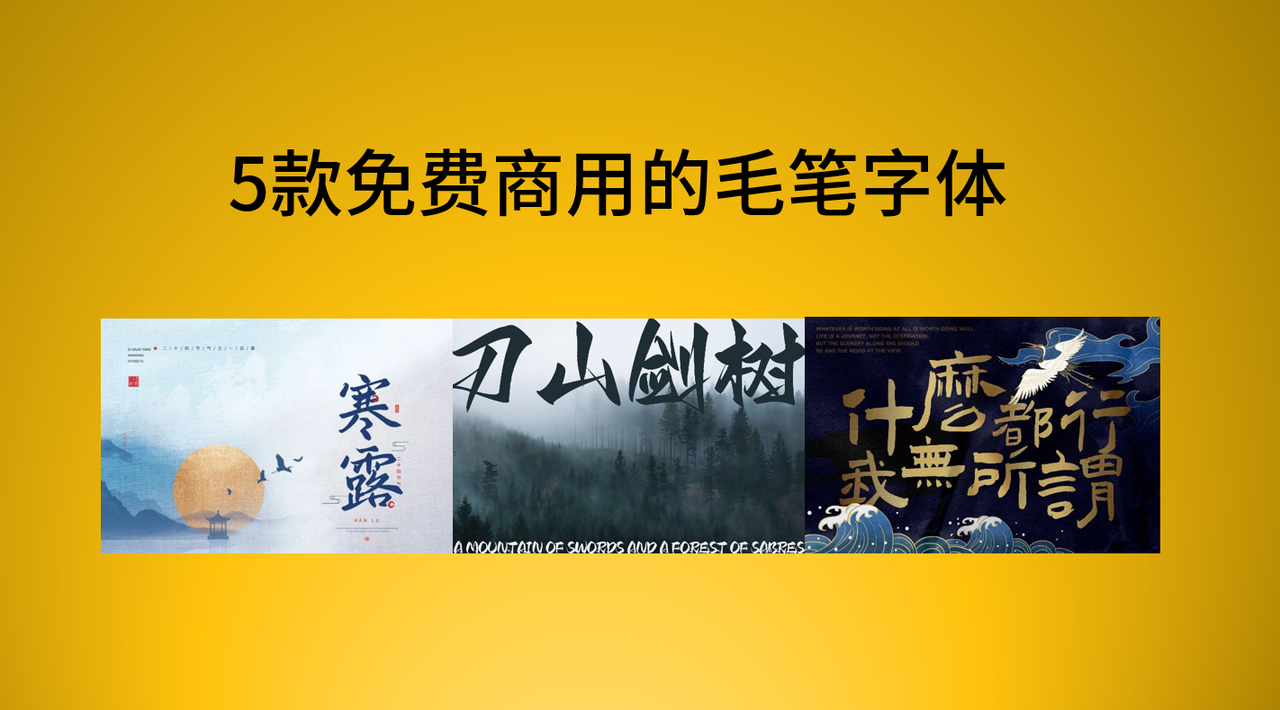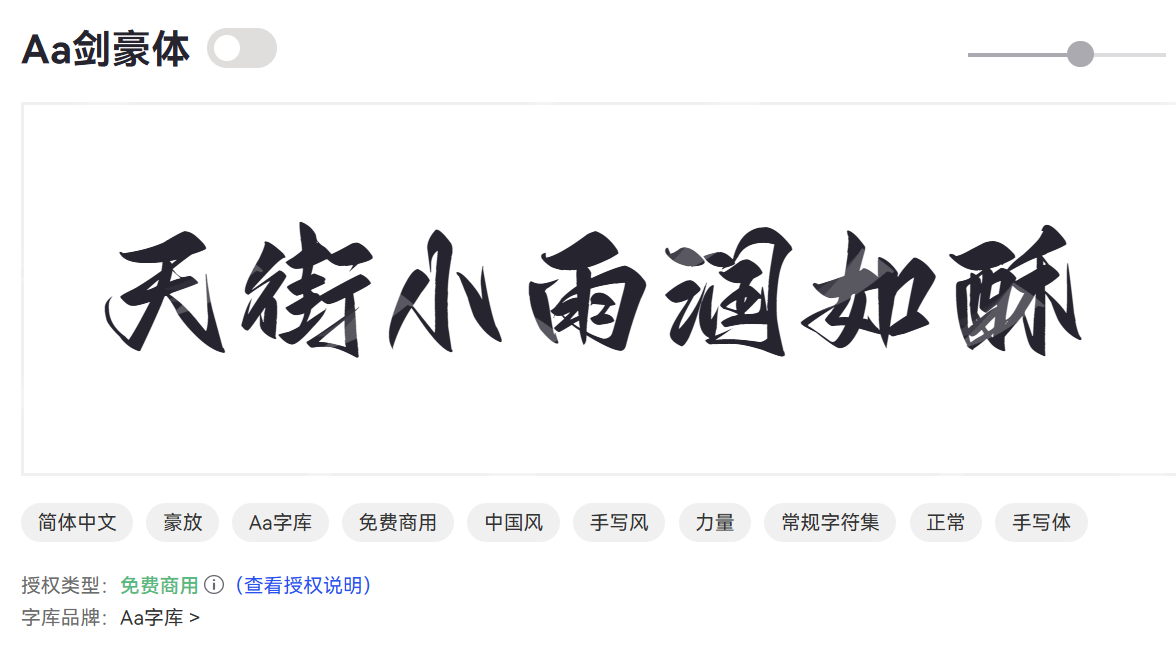
毛笔字体可以商用吗?5款可以免费商用的毛笔字体
毛笔字体是一种承载着深厚文化底蕴的字体,模仿中国传统毛笔书写风格的字体。很多小伙伴想使用毛笔字体,但怕不能商用。今天就给大家分享5款可以免费商用的毛笔字体。
5款免费商用的毛笔字体
演示佛系体
演示佛系体是一款以“佛系”生活态度为灵感的字体,笔画圆润、舒缓,整体风格平和、放松,传达一种随性、宁静的意境。
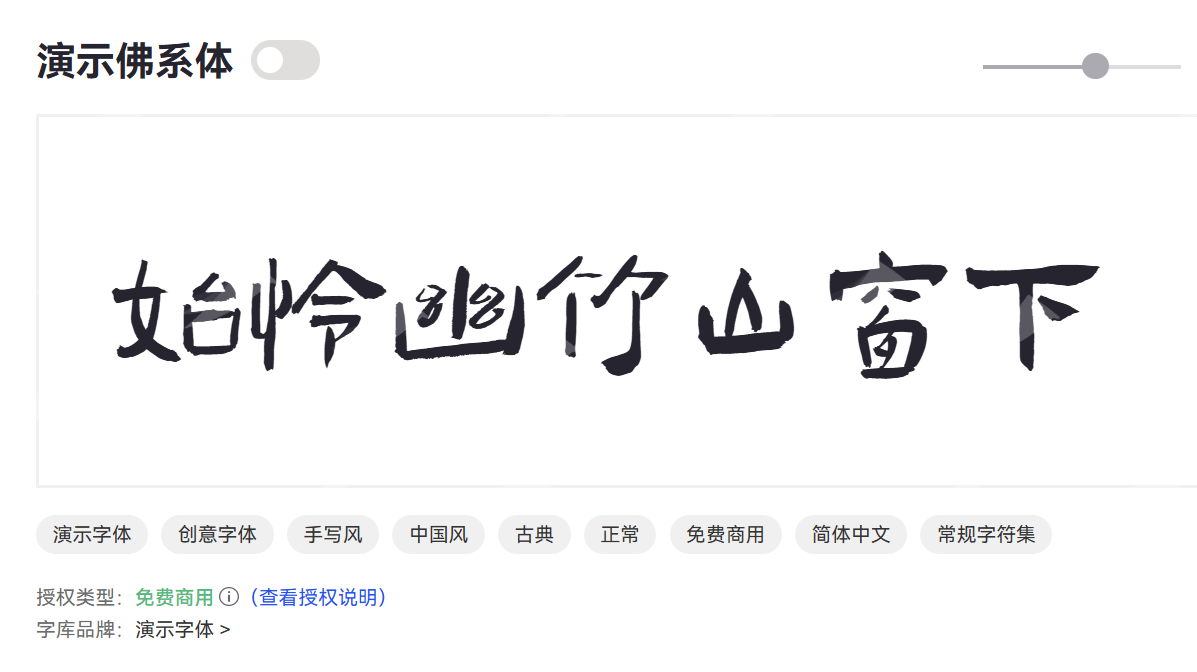
字体特点
- 笔画末端和转折处多采用圆角处理,减少了棱角感。
- 字形结构松散而不失整体感,笔画粗细变化柔和。
使用场景
- 咖啡馆、茶馆、瑜伽馆、健康养生类的宣传品。
- 诗歌、散文、短文的排版,或作为艺术设计中的辅助字体。
- 冥想App、放松音乐专辑封面等。
Aa剑豪体
Aa剑豪体是一款充满力量感和动感的创意字体,笔画硬朗、锐利,带有独特的“剑气”或“刀锋”般的锋芒,适合需要强调魄力与速度感的场景。
字体特点
- 笔画粗壮有力,多采用直线和锐利的折角。
- 字形设计中融入了刀剑的元素,如锐利的收笔或尖锐的转折。
- 整体风格充满爆发力,给人一种向前冲刺的感觉。
使用场景
- 体育赛事海报、运动品牌宣传、电竞相关设计。
- 电影海报、游戏宣传、动作片标题。
- 强调力量、速度、挑战的科技、汽车或户外品牌。
- 适用于需要表现突破、前沿的科技类设计。
平方赖江湖琅琊体
平方赖江湖琅琊体是一款将宋体结构与武侠江湖的洒脱、不羁风格相结合的字体,字形方正而不失灵动,带有独特的东方韵味和侠气。
字体特点
- 整体字形偏向方正,稳重而有力量。
- 东方美学: 结合了中国传统书法的韵味,特别是宋体或行书的特征。
使用场景
- 武侠题材的游戏、影视剧、小说、动漫的标题和宣传。
- 传统工艺品、中式餐饮、文化旅游等。
- 历史纪录片、博物馆展览、古代场景设计。
- 具有中国风元素的各类设计项目。
鸿雷行书简体
鸿雷行书简体是一款具有强大视觉冲击力的毛笔字体,笔画如鸿雷般磅礴、有力,线条流畅而充满力量感,常用于需要突出气势和力量的标题设计。
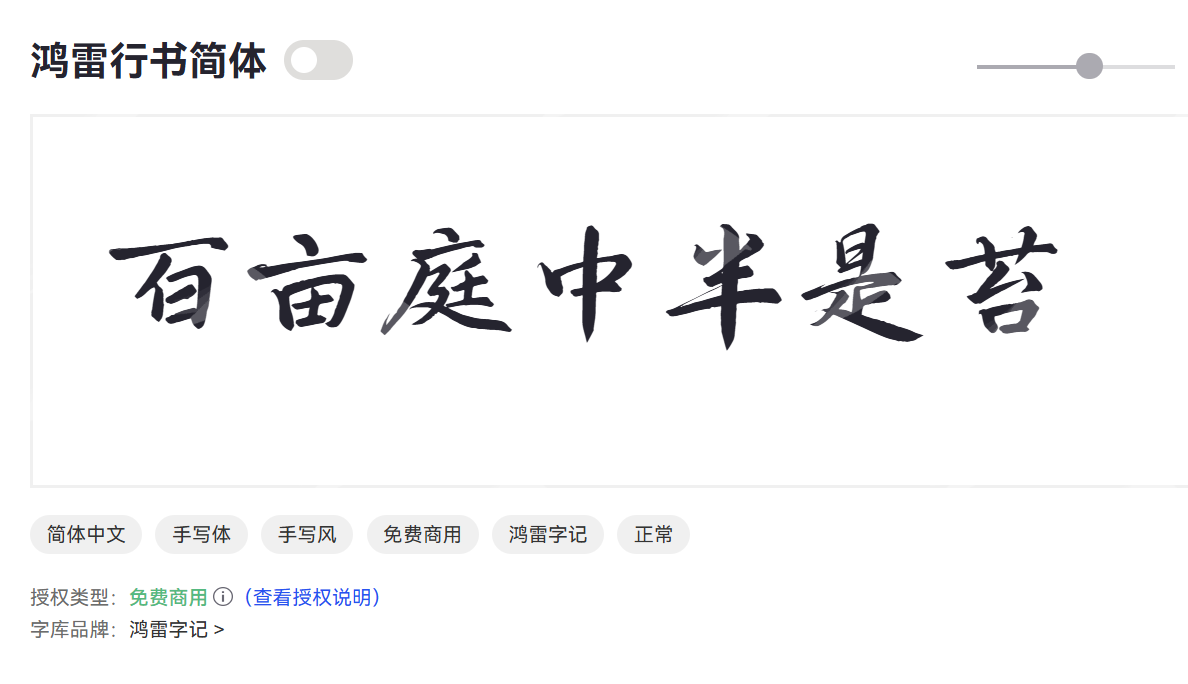
字体特点
- 字形开阔,笔画粗壮有力,具有强烈的视觉压迫感。
使用场景
- 庆典主题、赛事名称、大型展会标题。
- 用于展示企业宏大愿景或强大实力的宣传物料。
字库星球飞扬体
字库星球飞扬体是一款充满活力、轻快而富有艺术感的毛笔字体,笔画舒展,字形跳跃,仿佛带着飞扬的姿态,常用于需要活泼、积极、创意感的场合。
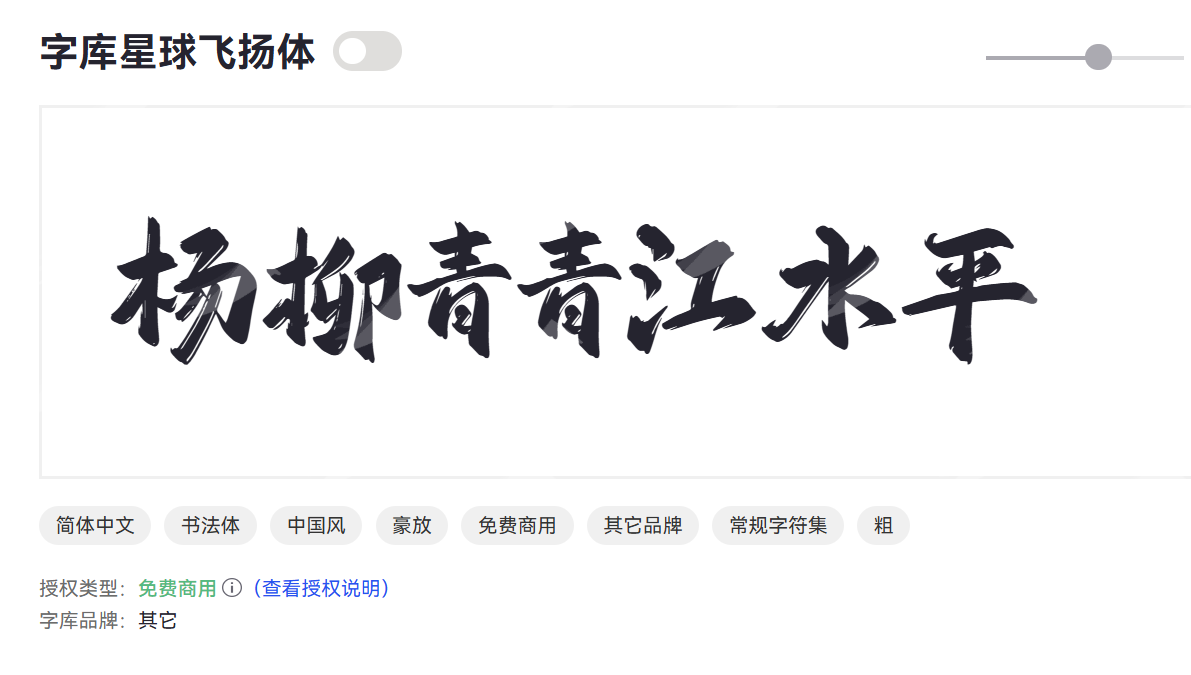
字体特点
- 笔画线条流畅,有向上延伸的趋势,显得轻盈。
- 字形结构设计感强,节奏感好,不显呆板。
- 带有一定的设计感和艺术笔触,使其区别于普通字体。
使用场景
- 服装品牌、时尚杂志、潮流活动宣传。
- 广告、海报、包装,尤其适合年轻化、有创意的产品。
- 网站标题、App界面、社交媒体内容。